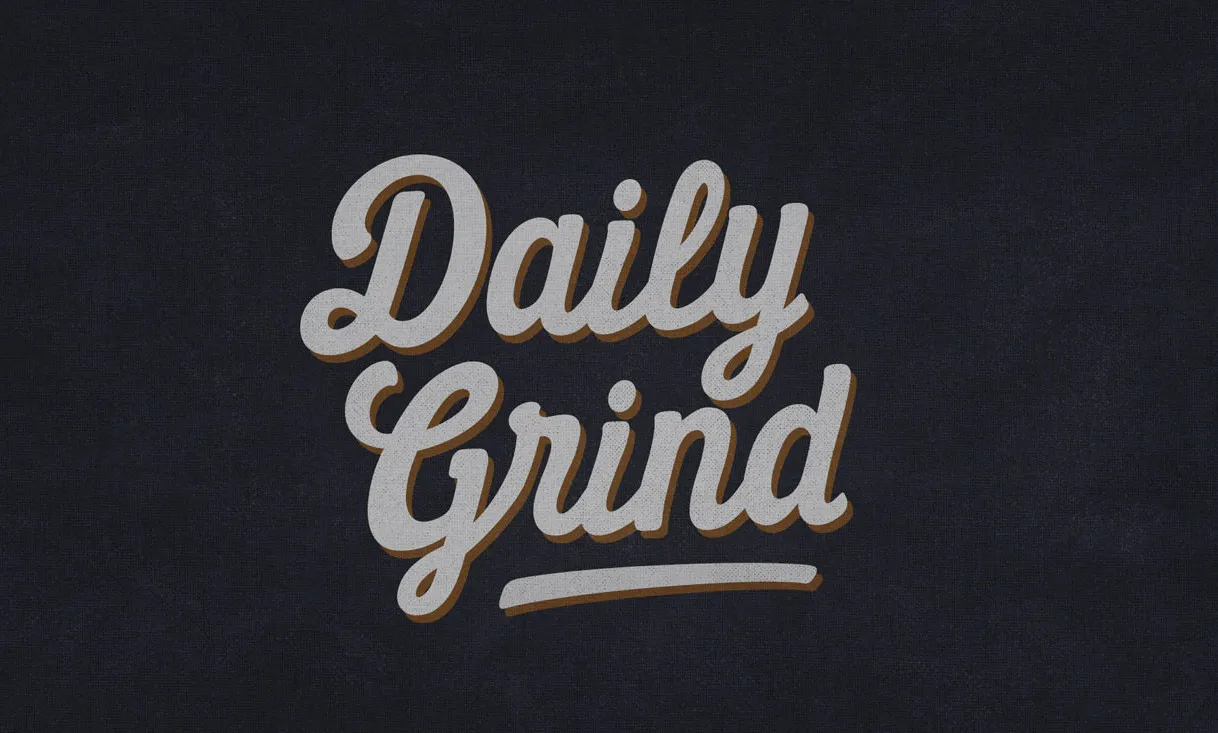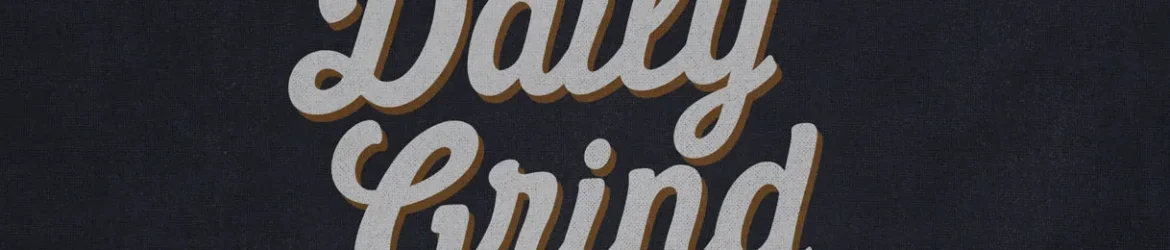
Daily Grind Script Font – Download Grátis
Introduzimos Daily Grind Script Font, criado pela designer blkbktyp. Esse tipo moderno, delicado e elegante é perfeito para diversas aplicações como cartões de convite para casamentos, logomarcas de sites, posts no Instagram, frases e todos os seus projetos lindos. Daily Grind Script traz um toque sofisticado às suas criações sem deixar de ser alegre e versátil, tornando-o uma escolha inteligente para um amplo leque de usos. Que tal adicionar mais elegância à sua próxima peça visual?